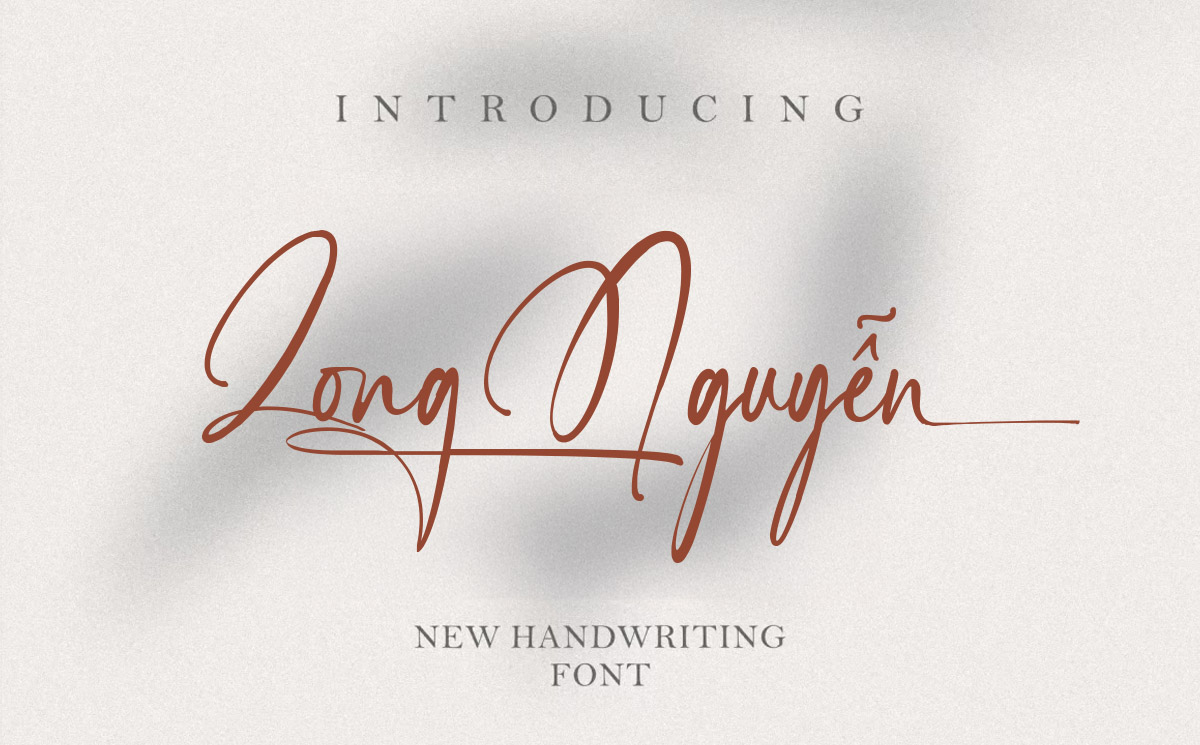
Top font chữ đẹp cho bao bì sản phẩm: mỹ phẩm, đồ ăn, thời trang
Gợi ý font TH Việt hóa đẹp cho bao bì sản phẩm: mỹ phẩm, đồ ăn, thời trang, nhãn mác, hộp giấy, tem nhãn và branding.
Bao bì là điểm chạm đầu tiên giữa sản phẩm và khách hàng. Trước khi người mua đọc kỹ thành phần, giá trị thương hiệu hay câu chuyện sản phẩm, họ thường bị thu hút bởi màu sắc, hình ảnh và font chữ trên nhãn mác. Một font bao bì sản phẩm phù hợp có thể khiến hộp mỹ phẩm trông cao cấp hơn, gói đồ ăn trở nên ngon mắt hơn hoặc tag thời trang có cá tính rõ hơn.
Khác với poster hoặc bài social, thiết kế bao bì có nhiều ràng buộc hơn: diện tích nhỏ, nhiều thông tin bắt buộc, chất liệu in đa dạng và yêu cầu đọc rõ ở khoảng cách gần. Vì vậy font packaging không chỉ cần đẹp. Font còn phải hỗ trợ tiếng Việt tốt, giữ được độ đọc khi in nhỏ, không quá mảnh trên chất liệu giấy hoặc decal, và phù hợp với phân khúc sản phẩm.
Bài viết này gợi ý các font TH Việt hóa đẹp cho bao bì mỹ phẩm, đồ ăn, thời trang, nhãn mác và nhận diện thương hiệu. Mỗi font có link tải và ảnh preview từ Fontdep.vn để bạn chọn nhanh theo phong cách sản phẩm.
Cách chọn font cho bao bì sản phẩm
Font cho bao bì cần được chọn theo vai trò. Tên thương hiệu hoặc tên dòng sản phẩm có thể dùng font serif, display, script hoặc vintage để tạo cá tính. Phần thành phần, hướng dẫn sử dụng, dung tích, ngày sản xuất và địa chỉ nên dùng font dễ đọc hơn như sans serif hoặc serif gọn.
Bạn cũng cần nghĩ đến chất liệu. Font mảnh có thể rất đẹp trên màn hình nhưng khi in trên giấy kraft, decal mờ hoặc hộp có texture sẽ dễ mất nét. Font quá trang trí có thể nổi bật trên mặt trước nhưng không phù hợp cho thông tin phụ ở mặt sau.
Với sản phẩm tiếng Việt, hãy test dấu trước khi chốt. Các cụm như "dưỡng ẩm", "tẩy tế bào chết", "cà phê rang xay", "bánh quy bơ", "áo khoác nữ" sẽ giúp bạn phát hiện nhanh lỗi dấu, lỗi khoảng cách và chữ bị fallback.
Font bao bì mỹ phẩm, đồ ăn và thời trang khác nhau thế nào?
Bao bì mỹ phẩm thường cần cảm giác sạch, sang, tin cậy hoặc nữ tính. Serif thanh lịch, sans serif tối giản và script nhẹ có thể tạo cảm giác premium. Tuy nhiên phần thành phần và công dụng vẫn cần font rõ để khách đọc được.
Bao bì đồ ăn cần gợi vị giác và sự thân thiện. Font retro, vintage, handwriting hoặc display đậm có thể giúp sản phẩm nổi bật trên kệ. Với thực phẩm thủ công, font mộc mạc và hoài cổ thường tạo cảm giác tự nhiên hơn.
Bao bì thời trang cần thể hiện gu thương hiệu. Thời trang tối giản hợp sans serif sạch; boutique nữ tính hợp serif hoặc chữ ký; streetwear hợp font display cá tính. Tag quần áo, nhãn dệt và hộp đóng gói nên kiểm tra kỹ độ rõ ở kích thước nhỏ.
Top font chữ đẹp cho bao bì sản phẩm
Danh sách dưới đây ưu tiên các font TH Việt hóa có thể dùng cho nhiều nhóm sản phẩm. Bạn có thể dùng font nổi bật cho mặt trước bao bì, sau đó phối với font dễ đọc hơn cho thông tin phụ.
1. TH Valoer
TH Valoer là font thẩm mỹ, sang và sạch, hợp bao bì mỹ phẩm, spa, skincare, hộp quà, nhãn chai serum và các thương hiệu beauty cần cảm giác tinh tế. Khi dùng cho bao bì, hãy test thử tên sản phẩm, dung tích, thành phần và một đoạn mô tả ngắn để đảm bảo font rõ ở kích thước in thật.
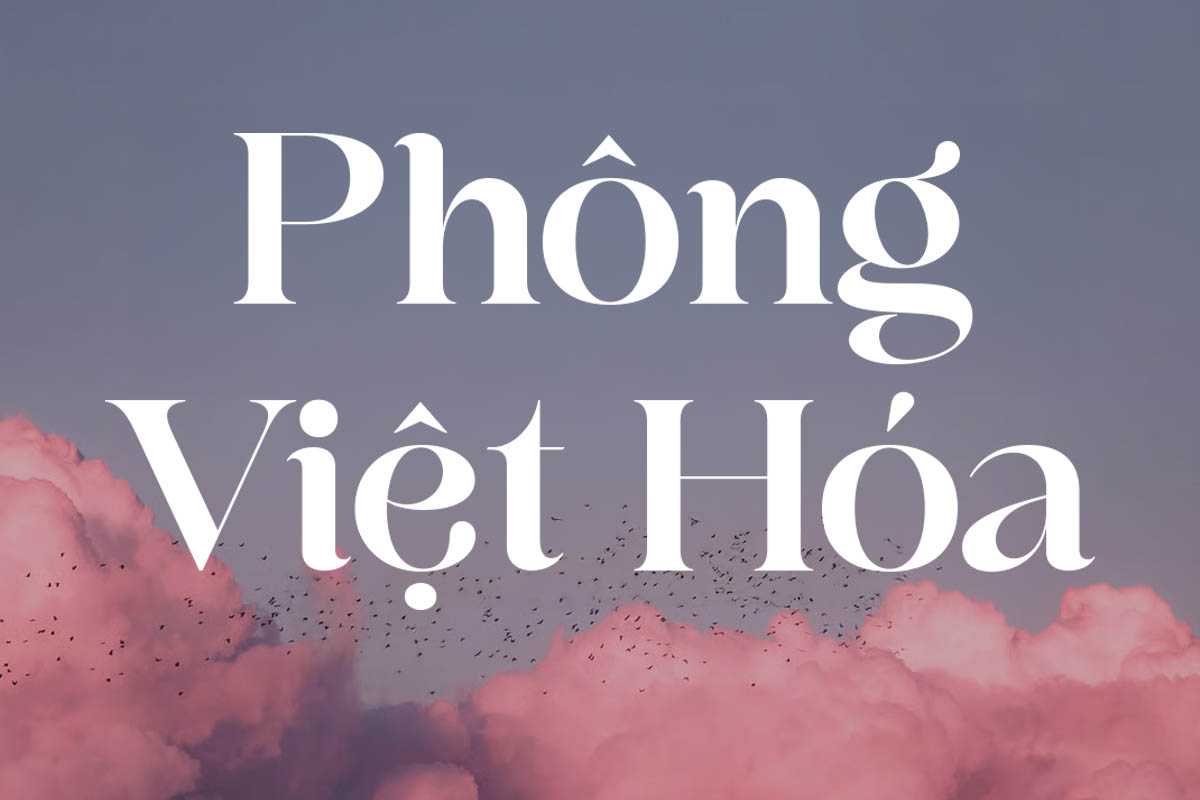
2. TH Spa/My Pham
TH Spa/My Pham là bộ font dành cho spa và mỹ phẩm, dễ dùng khi thiết kế nhãn sản phẩm chăm sóc da, menu dịch vụ, hộp giấy và bài social ra mắt sản phẩm. Khi dùng cho bao bì, hãy test thử tên sản phẩm, dung tích, thành phần và một đoạn mô tả ngắn để đảm bảo font rõ ở kích thước in thật.
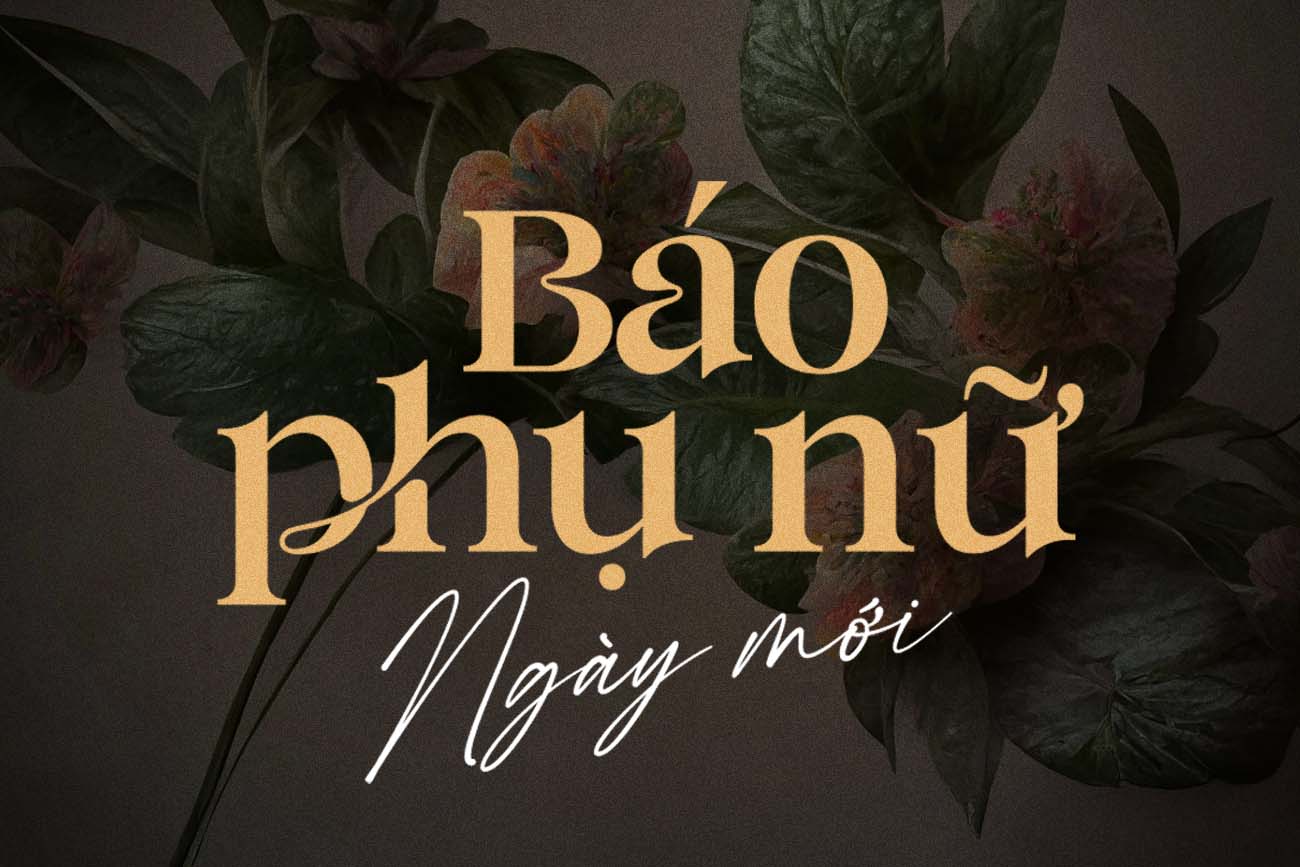
3. TH Selvia Genatu
TH Selvia Genatu là font serif sang trọng, phù hợp bao bì nước hoa, mỹ phẩm cao cấp, thời trang, hộp quà premium và các nhãn mác cần cảm giác editorial. Khi dùng cho bao bì, hãy test thử tên sản phẩm, dung tích, thành phần và một đoạn mô tả ngắn để đảm bảo font rõ ở kích thước in thật.
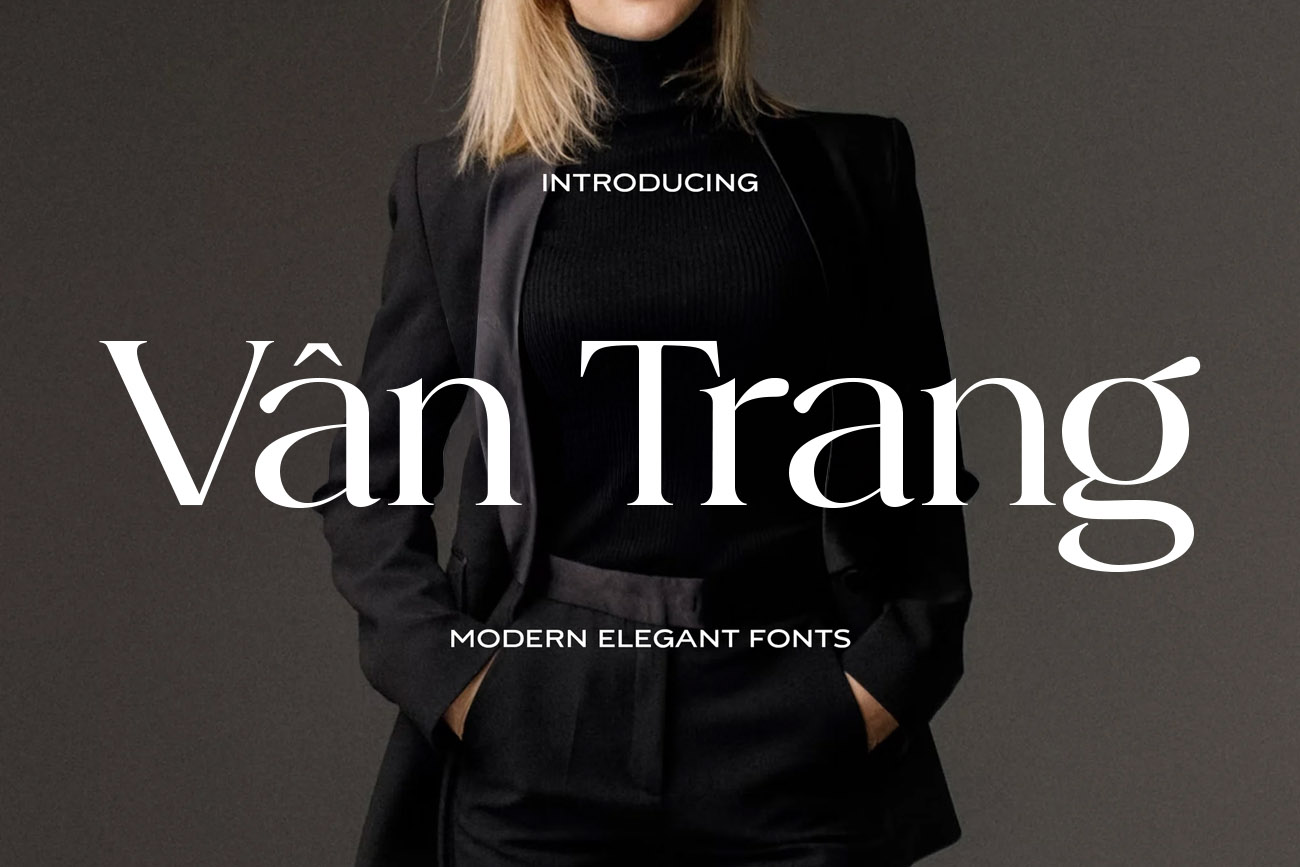
4. TH Revans Serif
TH Revans Serif là font serif cổ điển hiện đại, hợp nhãn thực phẩm thủ công, hộp bánh, bao bì trà, cafe, rượu nhẹ và thương hiệu có nét tin cậy. Khi dùng cho bao bì, hãy test thử tên sản phẩm, dung tích, thành phần và một đoạn mô tả ngắn để đảm bảo font rõ ở kích thước in thật.
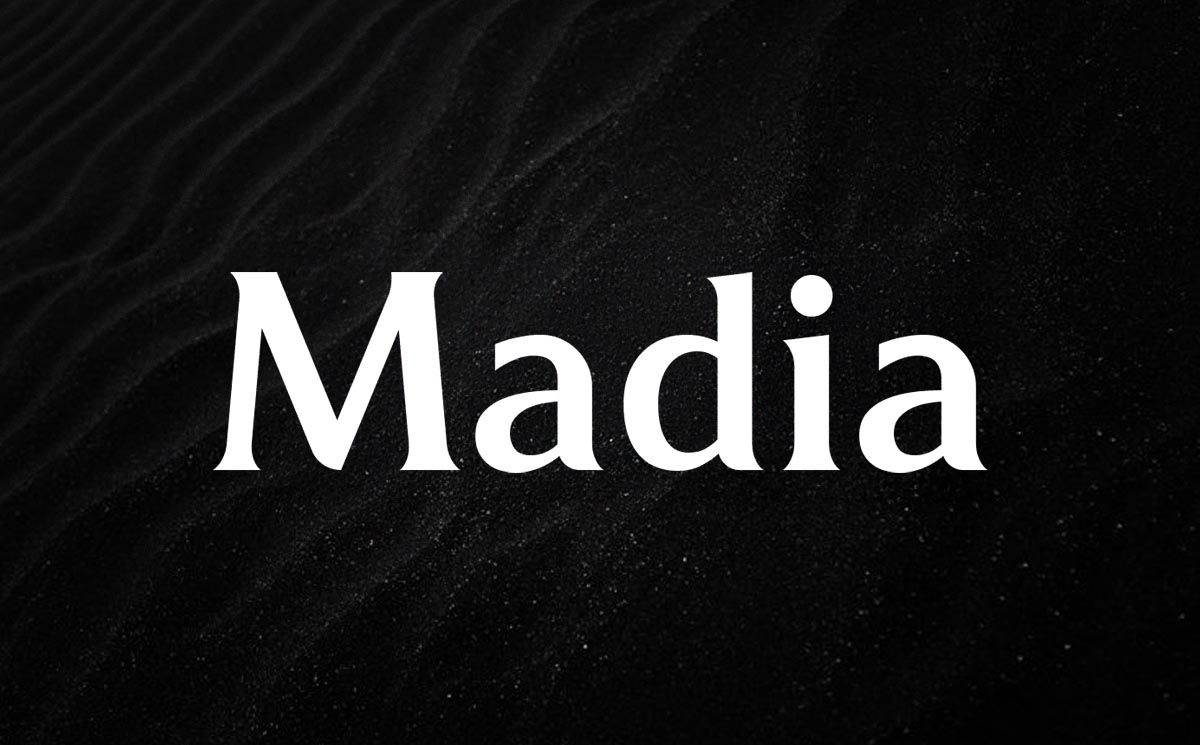
5. TH Vintoria
TH Vintoria là font vintage cao cấp, phù hợp nhãn mác thời trang, hộp trang sức, sản phẩm quà tặng, bao bì premium và thương hiệu có hơi hướng cổ điển. Khi dùng cho bao bì, hãy test thử tên sản phẩm, dung tích, thành phần và một đoạn mô tả ngắn để đảm bảo font rõ ở kích thước in thật.
6. TH Romaben
TH Romaben là font vintage cổ điển, hợp bao bì cafe, chocolate, bánh ngọt, mỹ phẩm thiên nhiên và nhãn sản phẩm cần cảm giác có câu chuyện. Khi dùng cho bao bì, hãy test thử tên sản phẩm, dung tích, thành phần và một đoạn mô tả ngắn để đảm bảo font rõ ở kích thước in thật.
Font bao bì sản phẩm cần đẹp, đúng phân khúc và đủ rõ khi in thật. Với mỹ phẩm, ưu tiên sạch và sang; với đồ ăn, ưu tiên cảm giác ngon mắt và thân thiện; với thời trang, ưu tiên cá tính thương hiệu.
Các font TH Việt hóa trong bài là bộ gợi ý thực tế để bạn thiết kế nhãn mác, hộp giấy, tem sản phẩm, bao bì F&B, mỹ phẩm và thời trang. Hãy tải font phù hợp, test tiếng Việt kỹ và phối font theo đúng vai trò trên bao bì.